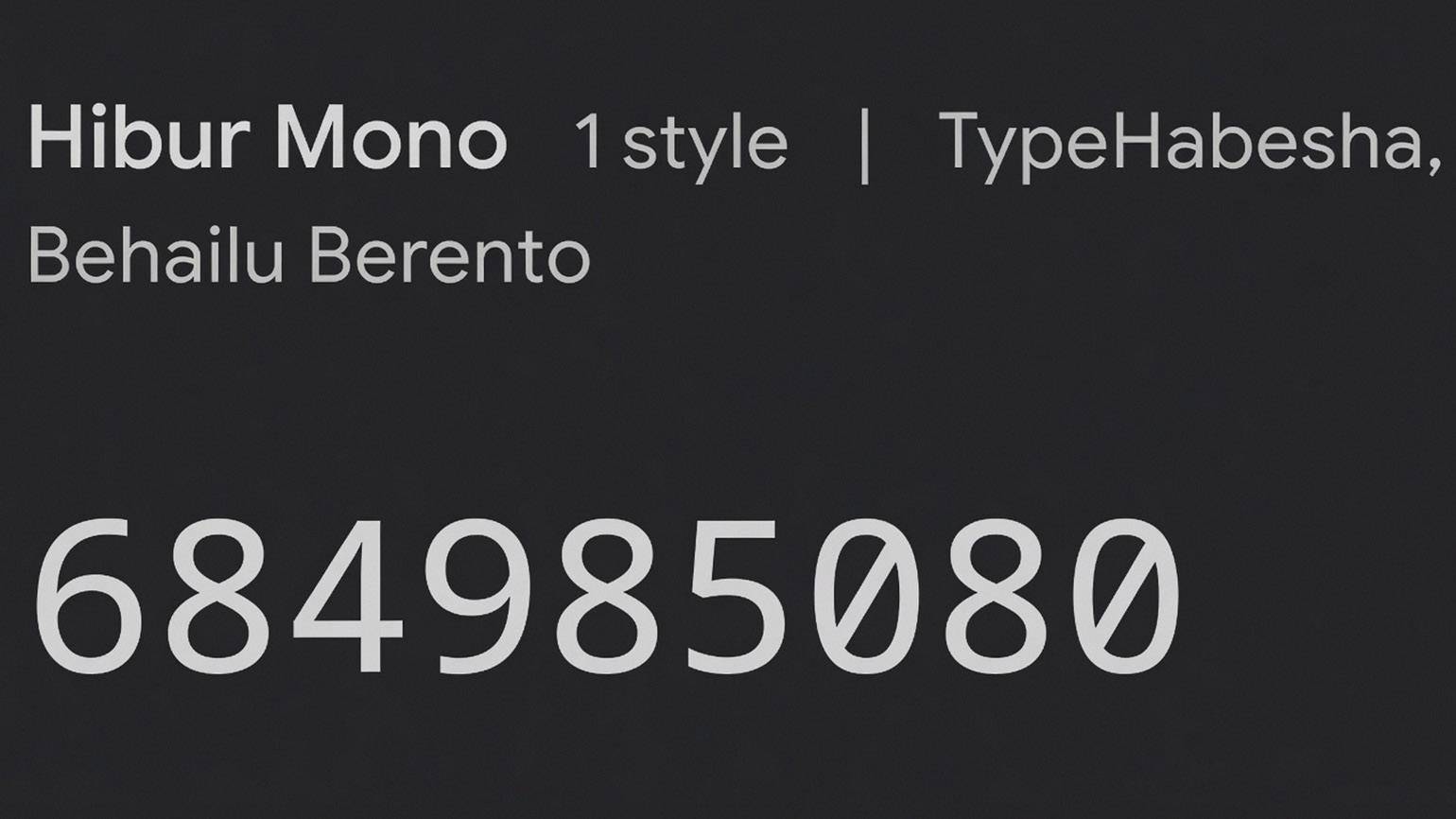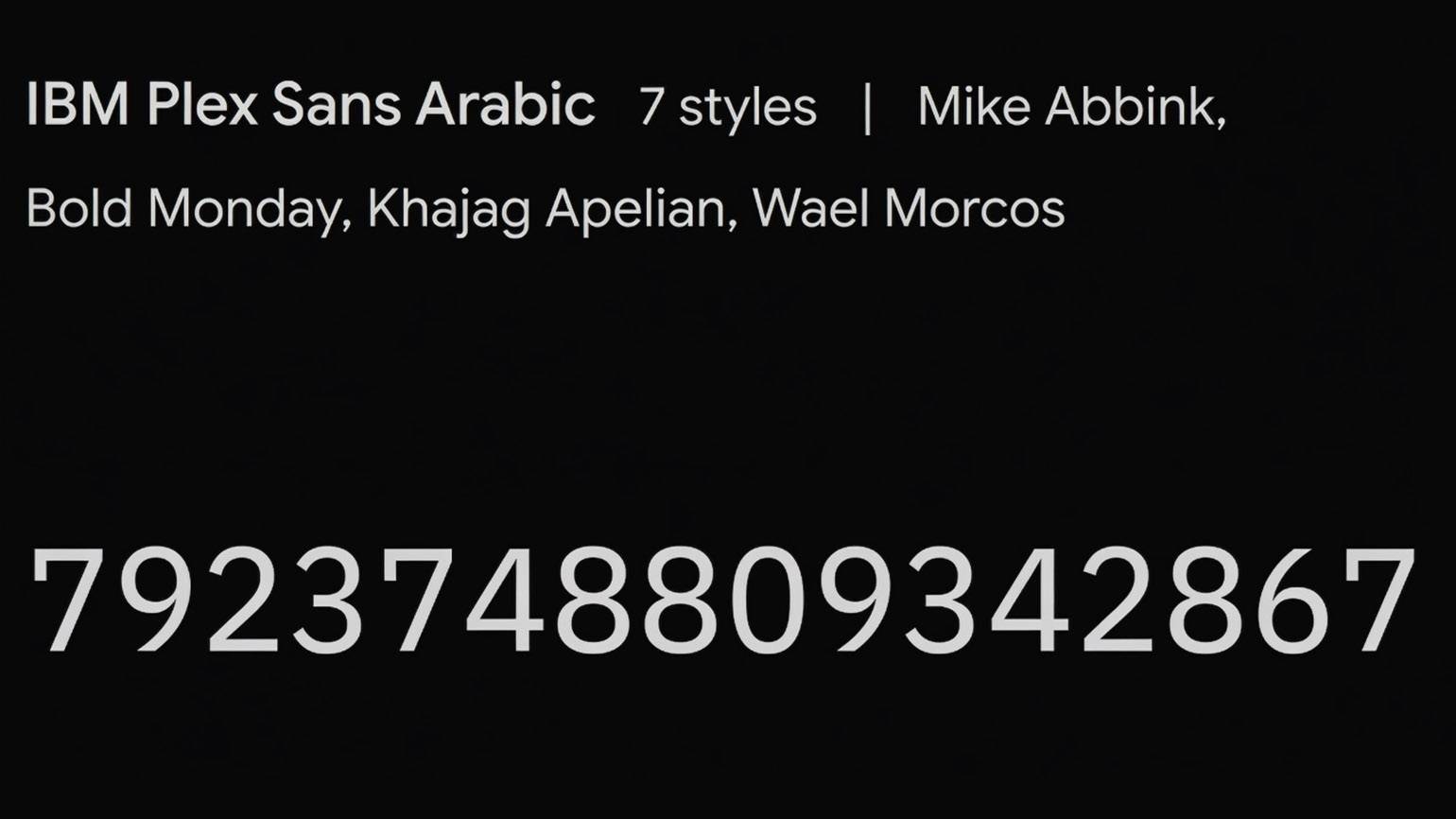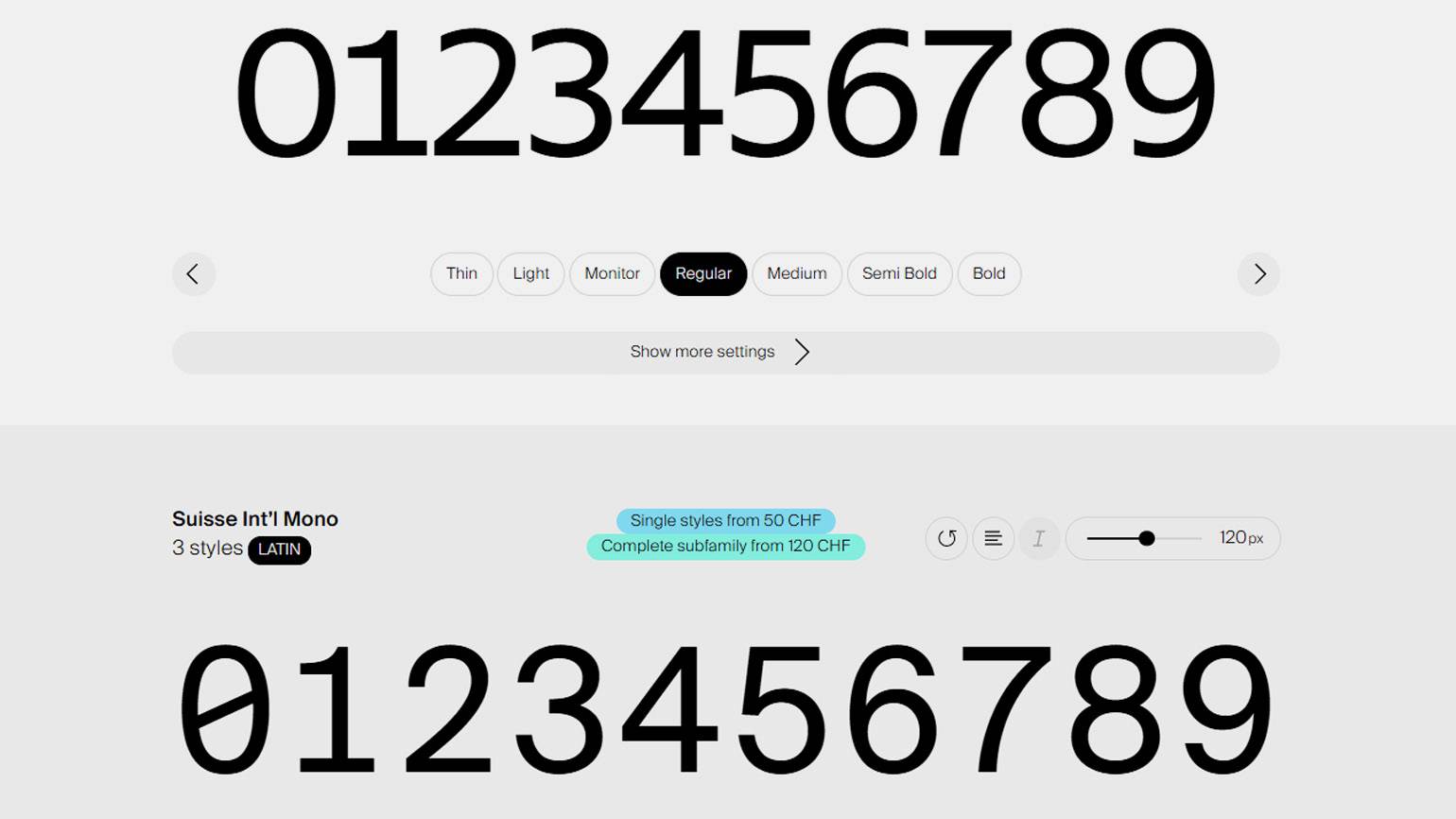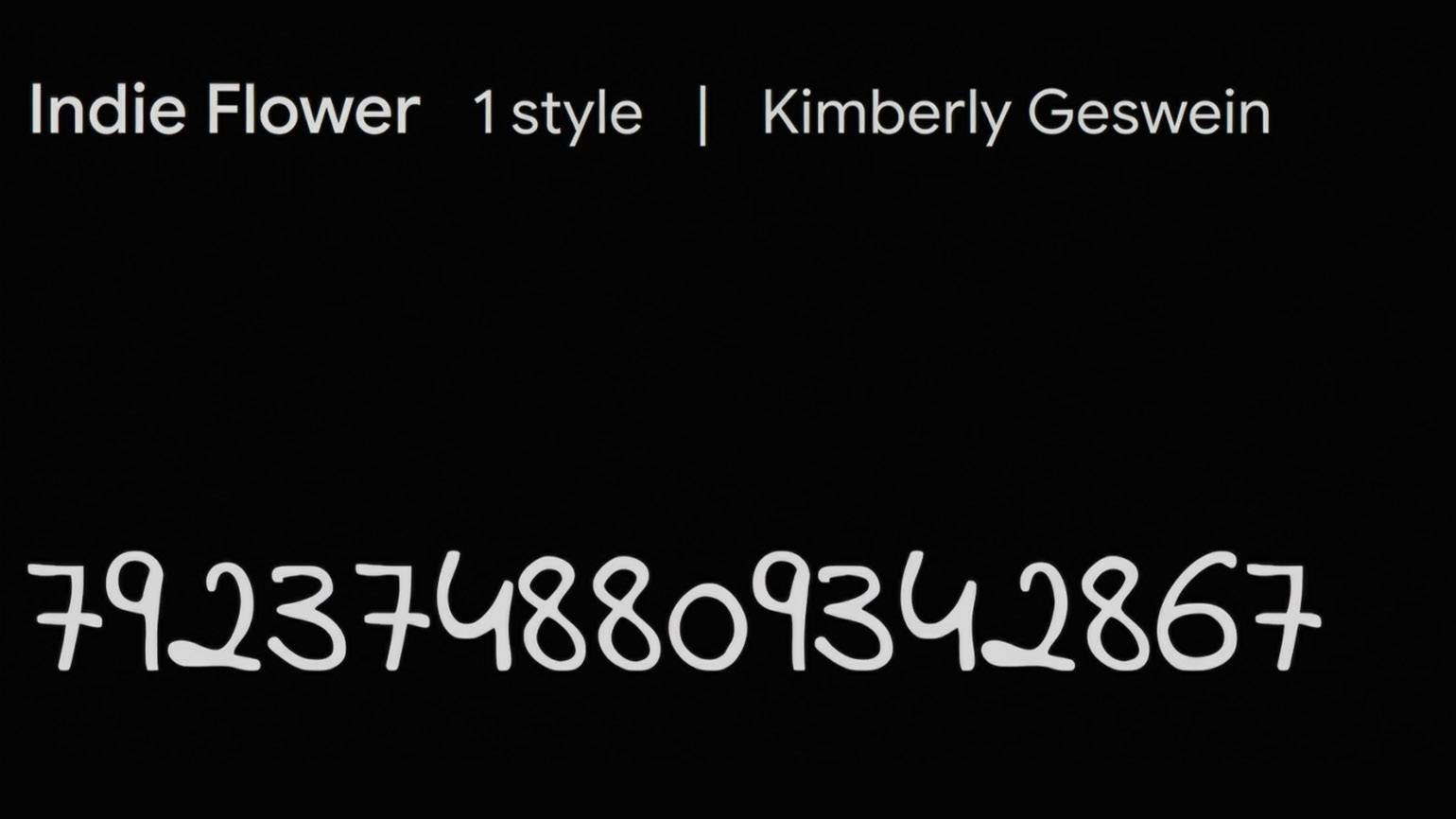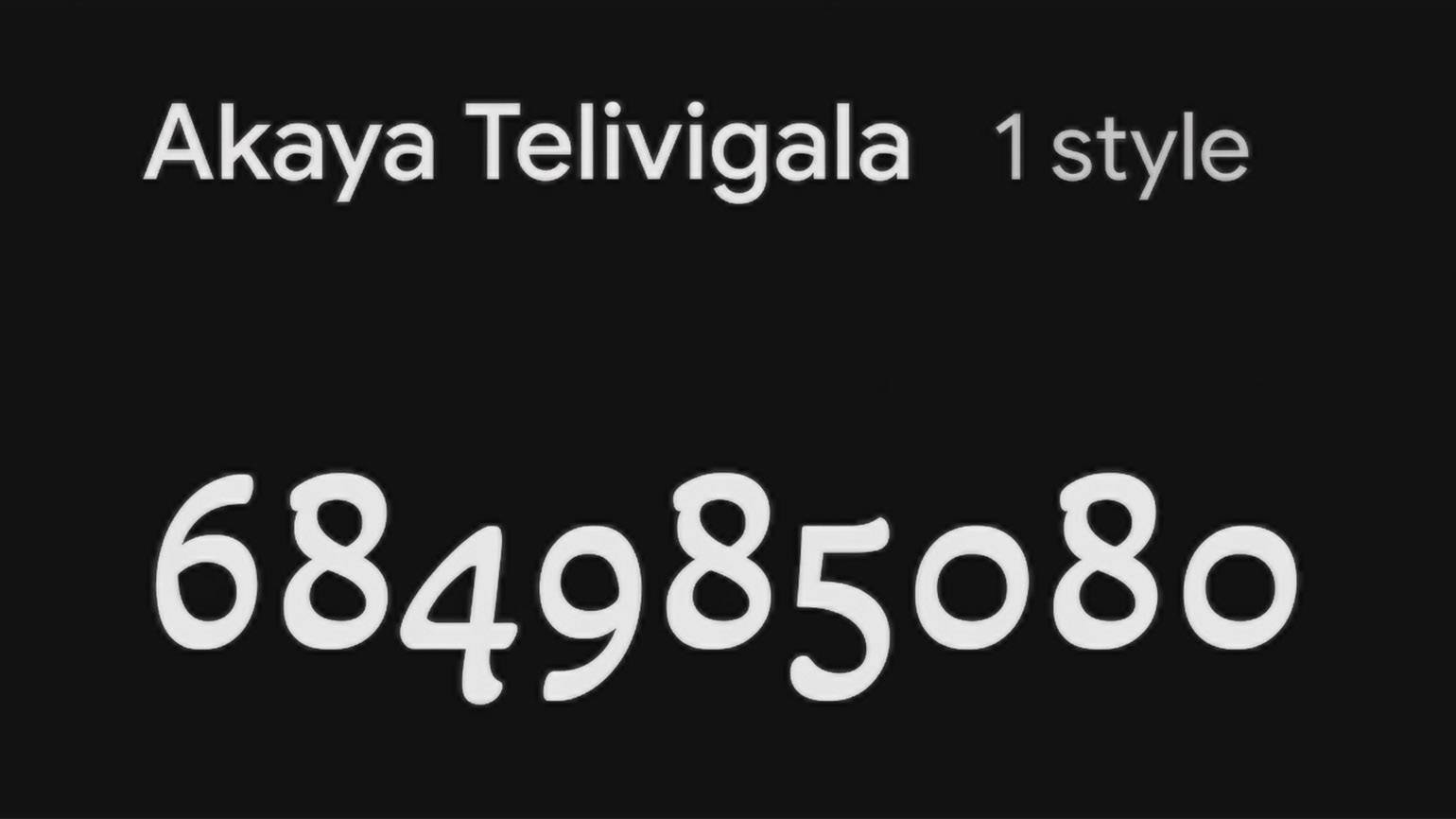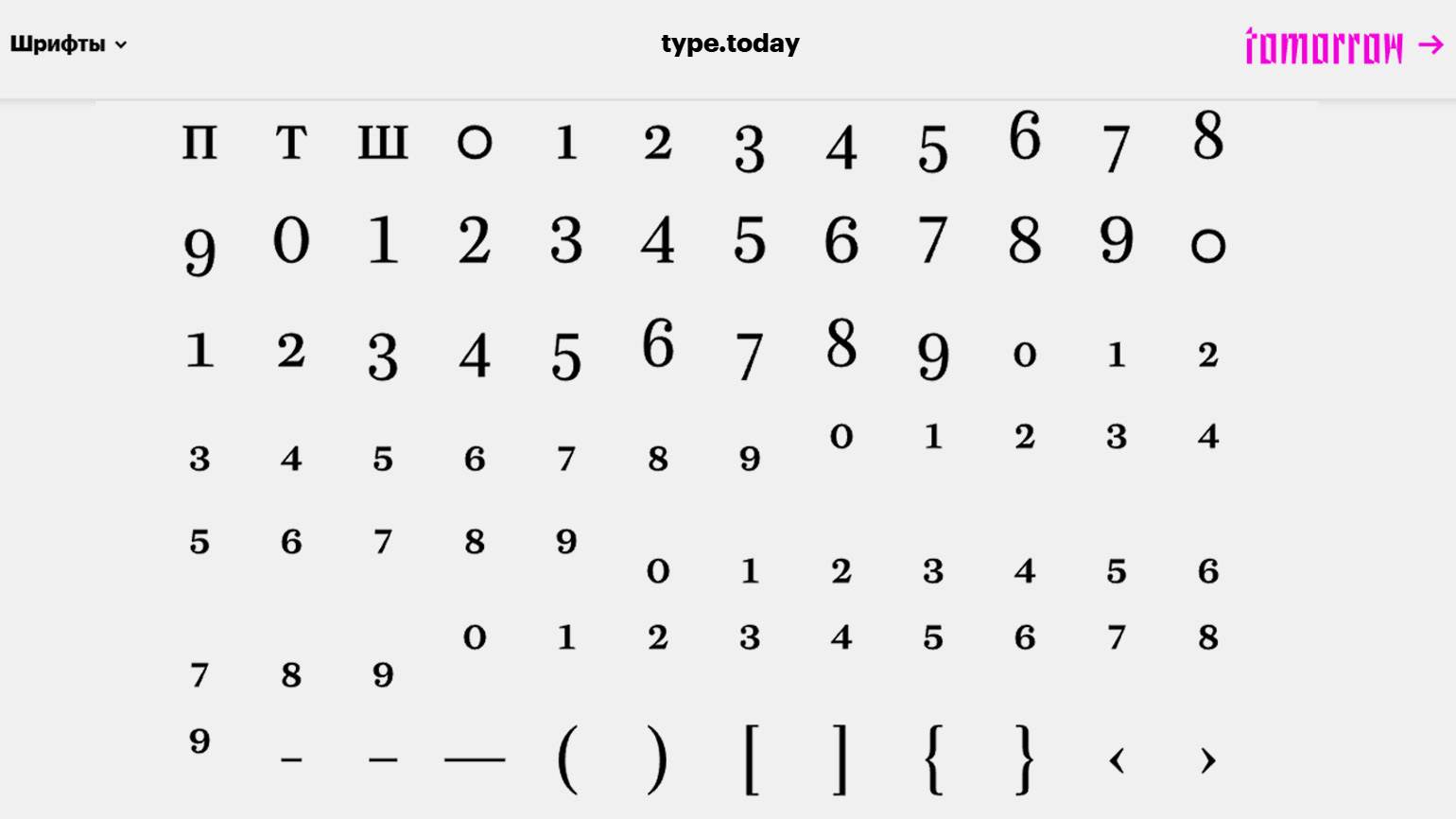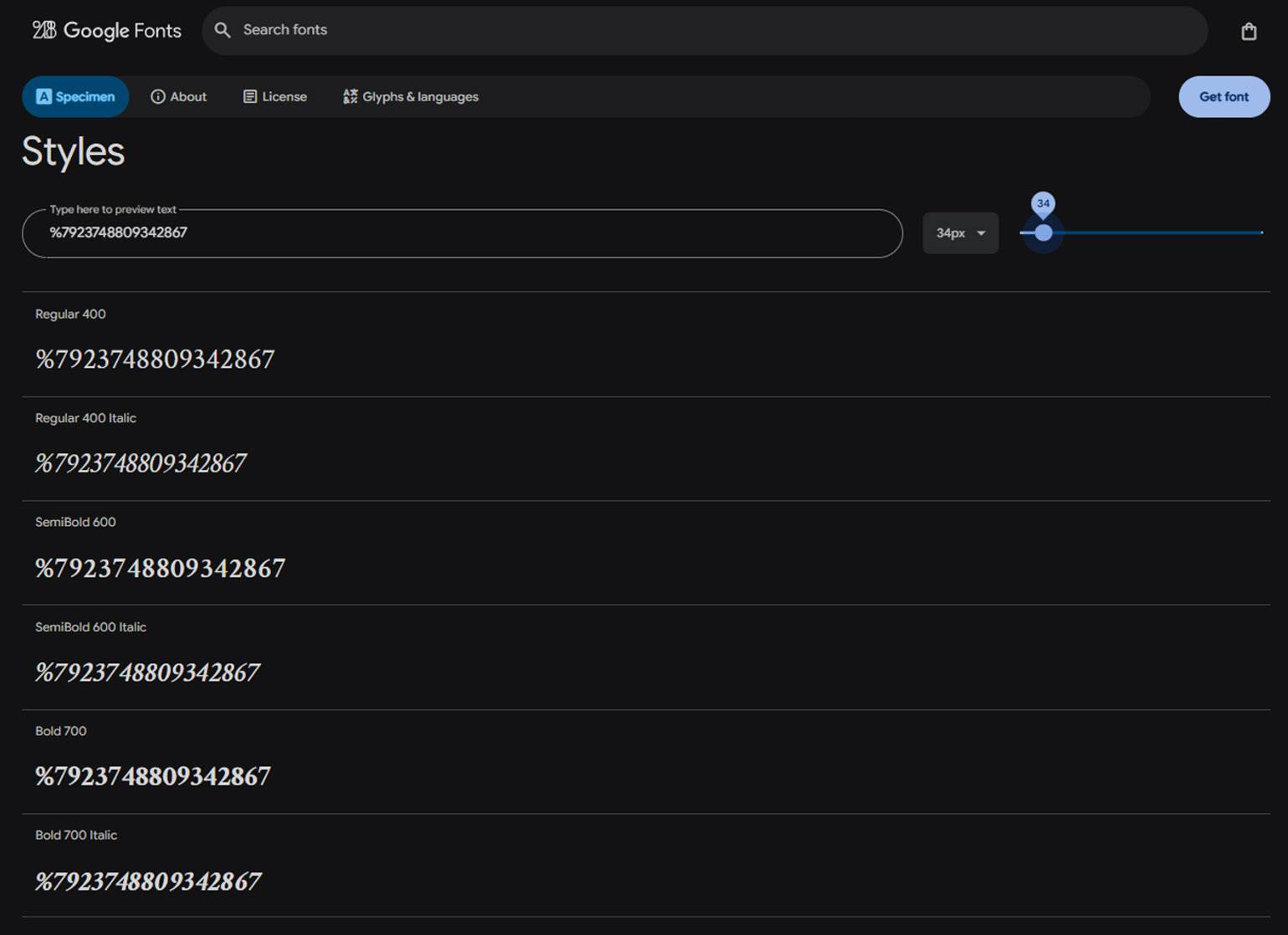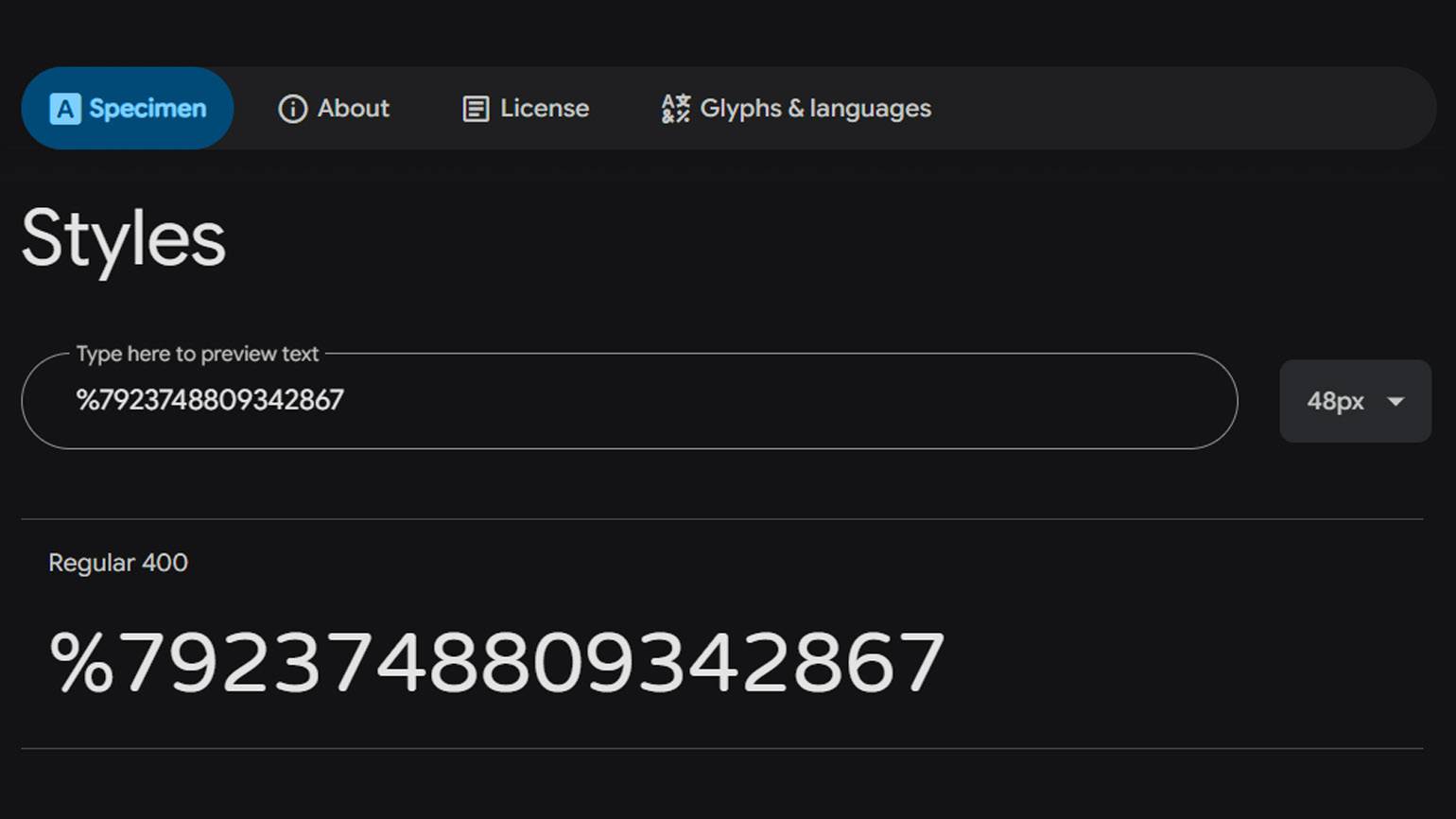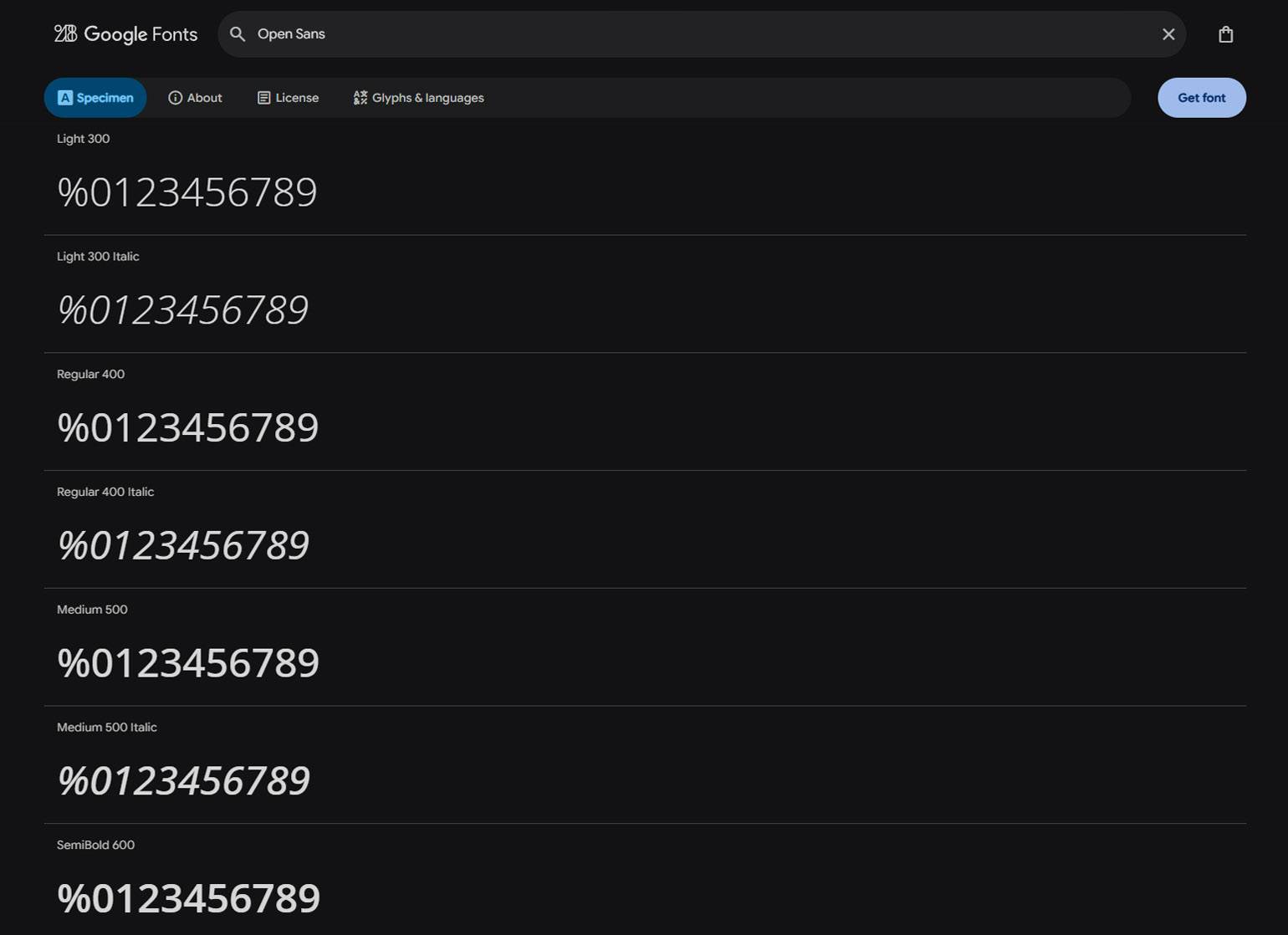
Лучшие бесплатные шрифты для цифр и чисел
На что обратить внимание при выборе шрифта для ценников и таблиц.
Шрифт может отлично работать в основном тексте, но оказаться неудачным для цифр. Из-за этого цены, даты, номера телефонов и данные в таблицах становится сложнее воспринимать, хотя сама гарнитура выглядит удачно. Поэтому при выборе шрифта дизайнеры оценивают не только буквы, но и цифры.
В статье разбираемся:
- какие вообще существуют виды шрифтов для цифр и чисел;
- на что важно обратить внимание при выборе;
- какие шрифты точно подойдут для разных задач;
- и какие шаги нельзя пропускать при выборе шрифта.
Какими бывают цифры в шрифтах
Большинство современных шрифтов включают полный набор цифр. Но это не значит, что все они выглядят одинаково: в одном шрифте может быть несколько вариантов начертания для разных задач — например, для сплошного текста, таблиц или финансовых документов.
Вспомним, на какие основные группы стилистически делятся шрифты:
- рубленые шрифты — без засечек;
- шрифты с лёгкими засечками — с несколько утолщёнными концами вертикальных штрихов;
- медиевальные — с небольшими засечками треугольной формы, иногда с небольшим наклоном округлых букв;
- обыкновенные шрифты — с тонкими длинными засечками и вертикальной осью букв;
- брусковые шрифты — неконтрастные или малоконтрастные, с длинными утолщёнными засечками в форме брусков;
- малоконтрастные шрифты — это шрифты, в которых разница между толщиной вертикальных и горизонтальных штрихов очень мала или почти незаметна, с длинными утолщёнными или закруглёнными засечками.
Цифры часто передают важную информацию — например, номер телефона или график работы. Чтобы их было легко читать, дизайнеры обычно выбирают шрифты с минимально заметными засечками или без них.
По типу оформления самих цифр шрифты делятся уже иначе.
Минускульные цифры (Old-style figures)
К минускульным относят начертания, у которых базовая высота цифр приближена к высоте строчных букв. У них могут быть выносные элементы: нижние у 3, 4, 5, 7, 9 и верхние у 6 и 8. Но в целом такие цифры не слишком отличаются от букв, поэтому их удобно использовать в макетах, где числа должны естественно встраиваться в текст — например, когда в материале много дат.
Маюскульные цифры (Lining figures)
У маюскульных цифр нет выносных элементов, а их высота — практически такая же, что и у заглавных букв. Дизайнеры выбирают такое начертание, чтобы сделать акцент именно на цифрах — например, при указании даты проведения мероприятия.
Если у шрифта по умолчанию есть две версии начертания — минускульные и маюскульные цифры, — то для переключения между ними в графических редакторах можно использовать операцию AllCaps.
Гибридные цифры (Hybrid figures)
Гибридные цифры можно использовать как для акцентов, так и в тексте. Обычно их высота — чуть больше, чем у строчных букв, а выносные элементы есть только у цифр 6 и 9.
Капительные цифры (Small caps figures)
Капитель — это начертание, в котором строчные буквы выглядят как уменьшенные заглавные. В случае если у шрифта есть такое начертание, для цифр тоже создают отдельную капительную вариацию. При этом они могут быть как маюскульными, так и минускульными.
Табличные и пропорциональные цифры (Tabular figures, Lining figures)
Другая важная классификация цифр — табличные и пропорциональные. Пропорциональные — это цифры, ширина которых может меняться в зависимости от дизайна знаков. Табличные цифры — всегда одной ширины.
Скриншот: Mike Abbink / Bold Monday / Khajag Apelian / Wael Morcos / Google Fonts / Skillbox Media
Скриншот: Kimberly Geswein / Google Fonts / Skillbox Media
Табличные цифры лучше всего подходят для использования подряд, например при указании номеров телефонов или в прайс-листах. Они легче воспринимаются, с ними удобнее работать в вёрстке. В то время как пропорциональные больше похожи на буквы и хорошо смотрятся внутри текста.
Как выбрать шрифт для цифр
Часто у компаний уже есть утверждённый шрифт для цифр или для материалов, содержащих цифры. Но если выбираете с нуля, можно обратиться к ряду рекомендаций, которым часто следуют дизайнеры и креативные агентства.
- Проверьте, равны ли цифры по высоте и ширине — часто дизайнеры заранее выбирают табличные шрифты без выносных элементов, так как они наиболее читабельны.
- Убедитесь, что в шрифте есть все специальные элементы для работы с числами — в гарнитуре может не оказаться знака процента, дробей или их начертание будет отличаться от остального шрифта.
После того как вы выбрали шрифт, проверьте лицензию. Даже если шрифт лежит в Google Fonts как бесплатный, у него могут быть особенности использования в разном контенте — например, запрет на размещение в коммерческих материалах.
Главное — помните, что универсальных шрифтов не бывает. Конечно, можно взять уже утомившие в интерфейсах Roboto, в инфографике IBM Plex Sans или JetBrains Mono, а в афишах Manrope. Они хорошо работают и выполняют свои задачи. Но сейчас дизайнеры создают огромное количество шрифтов, многие из которых бесплатны. Самое время попробовать что-то новое.